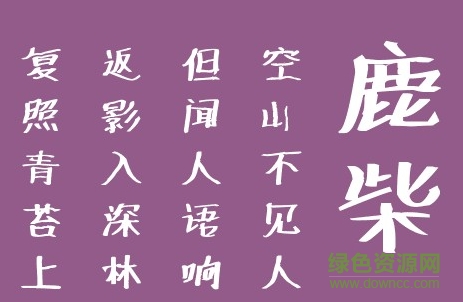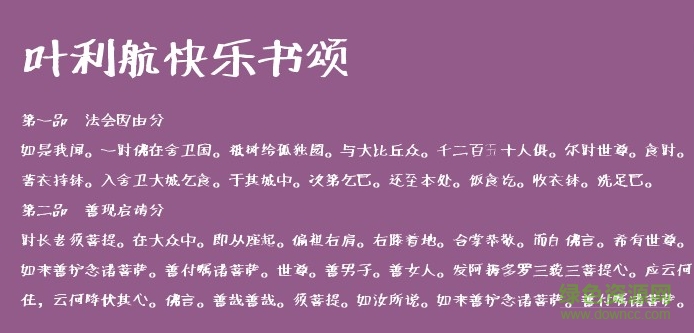
葉利航快樂書頌字體是一款非常有特色的兒童字體,這款字體形象新穎可愛,非常適用于兒童圖書、黑板報(bào)等領(lǐng)域。喜歡這款字體的朋友可以來綠色資源網(wǎng)下載使用喲!
葉利航快樂書頌是一款兒童字體,風(fēng)格突出,在保留最美的童真中,把漢字演繹為筆畫線條的頑皮,字型筆畫粗細(xì)不等,跳躍自然,適合用于兒童海報(bào)、卡通世界等載體上。